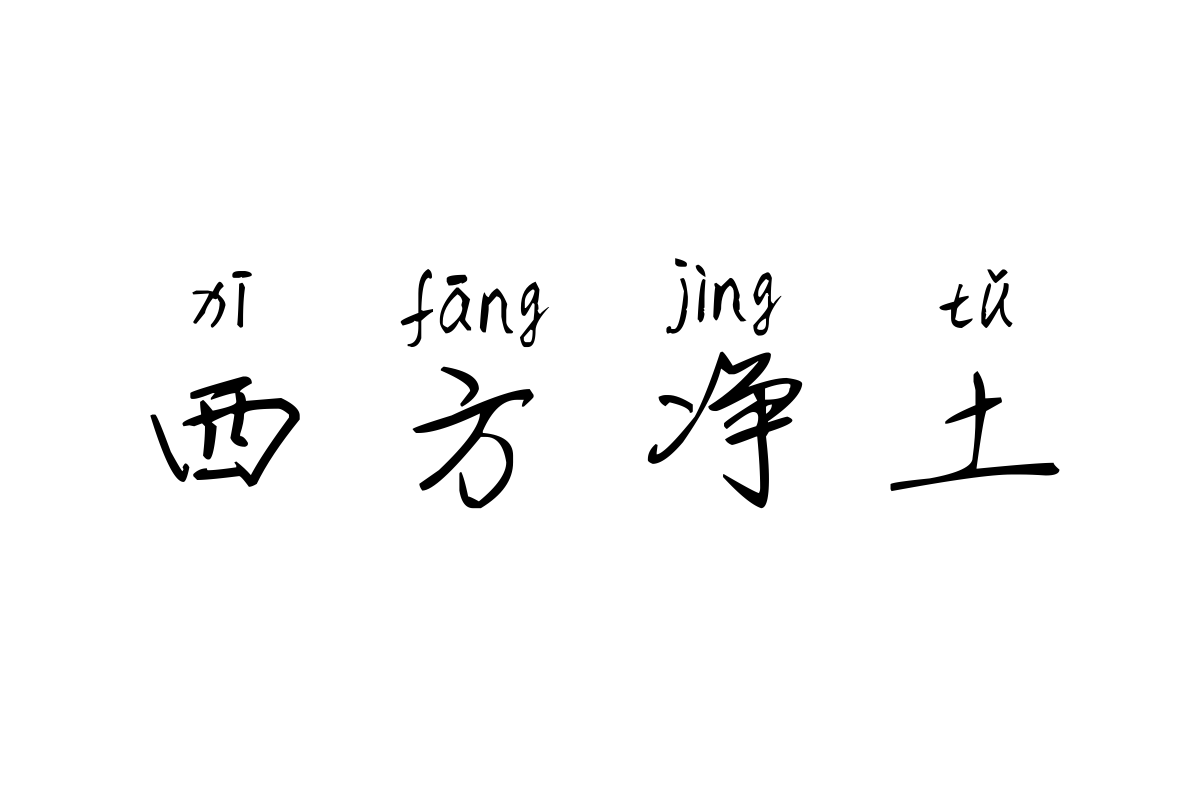
汉标灵秀拼音是一款具有独特风格的中文字体,其设计理念在于将现代感与古典美完美结合。这款字体采用了独特的笔画结构,使得每一个字符都显得既优雅又富有力量。
在设计上,汉标灵秀拼音采用了圆润的笔触,使得每个字符都显得更加柔和,同时也保留了一定的力度。这种设计使得整个字体既有古典的韵味,又不失现代感。
此外,汉标灵秀拼音还特别注重字形的平衡和对称性。在每个字符的笔画之间,都留有足够的空间,使得整个字体看起来既紧凑又不失开阔。这种设计使得整个字体既有美感,又易于阅读。
总的来说,汉标灵秀拼音是一款非常独特且具有艺术感的中文字体。无论是用于印刷还是电子显示,它都能展现出独特的魅力。